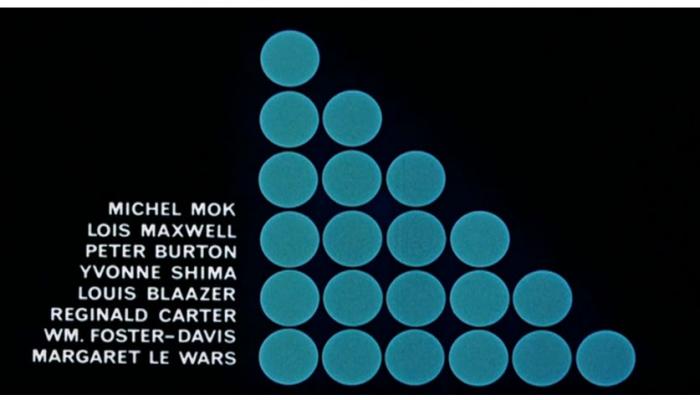
Akzidenz Grotesk geht schon in die richtige Richtung. Aber diese Titelei war damals alles Handarbeit. Eventuell wurde das Alphabet eigens gezeichnet und montiert, vielleicht gab es irgendwelche Fotosatz-Schablonen, wer weiß …
Dass man man jetzt einen heutigen Font benennen kann, der exakt diesen Look erzeugt, glaube ich eher nicht. Zumal die »Rounded-Charakter« ja wahrscheinlich kein Stilmittel sondern Folge der eingesetzten (Abfilm-)Technik war.
Dem J zu urteilen, handelt es sich um die »Gothic 720« von Bitstream und ist z.B. bei FontShop erhältlich.
Für die Gothic 720 finde ich auch nix, aber auch gar nix zum Schriftschneider. Ist die Gothic 720 einfach nur ein generischer Nachbau von den Schriften, wie sie auch im Titel verwendet wurden? Irgendwie erinnert die mich an die alten Monotype-Grotesken, welche auch die Basis für die Arial MT waren. Schon daher würde ich auf eine gewisse Verwandschaft tippen. Paar Schnitte der Gothic 720 findet man auch in jeder der Bitstream Sammlungen die Corel-Software (zB Draw) mitgeliefert wird.
Bitstream hat damals beim »Klauen« fremder Bibliotheken die Namen geändert und eben generische Begriffe with Geometric, Gothic usw. verwendet:
Gothic 720 (BT)
→ Grotesque 126, 215, 216
Gothic 725 (BT)
→ Akzidenz Grotesk
Gothic 762
→ Bell Centennial
Gothic 761
→ Bell Gothic
Gothic 821 (BT)
→  Block
Genau. Auch die Monotype Grotesque aus 1926 ist nicht ganz so originell wie sie uns häufig präsentiert wird. Sie war bei Monotype die Vorlage für die Arial, aber die Grotesque 215 und 216 basieren auf die Venus Grotesk der Bauer’sche Gießerei aus 1907. Das erzählt uns nicht nur der englische Schrifthistoriker James Mosley schon seit längerem, aber inzwischen auch Linotype. Hier noch ein Artikel von Paul Shaw mit ein paar interessante Abbildungen aus dem Leben der Monotype Grotesque und ihre Vorfahren, die Venus Grotesk und die Ideal Grotesk. Auch den Link auf Klimsch Jahrbuch 1907 ist verfolgenswert!
→ Grotesque 126, 215, 216
Die gibts aber nicht digital, oder?
Ich glaube schon, schau mal hier. Die Monotype Schriften haben heute halt keine Seriennummer mehr. Beispielsweise Times New Roman hatte zu Blei- und Fotosatzzeiten die Seriennummer 327. Ich vermute mal, dass sie danach verschwunden sind weil PostScript Type1 Schriften keine Nummern in bestimmte Nameneinträge enthalten konnten.
Hallo Pürsti. »Der Albert« sieht das so: damals war ich Angestellter der Firma Scangraphic. Mit der Klauerei hatte ich aber nicht viel zu tun, das Übel war im Grunde genommen bereits geschehen wo ich da angefangen habe. Inzwischen sind Gott sei Dank die Meisten der nicht-lizenzierten Schriften (das sind die die umbenannt und teilweise auch umgezeichnet wurden) vom Markt genommen worden.
Irgendwie klingt es als ob meinst dass Du zu lange auf eine Reaktion von mir warten musstet. Wenn Du es eilig hast, dann maile mich lieber persönlich, das geht bestimmt schneller.
Nein, hab es überhaupt nicht eilig. Hätt auch nicht nachgehakt wenn Du selber hier nicht recht streng gegen Bitstream geurteilt hättest. Warum Bitstream so als der ganz böse Bube immer hingestellt wird wo doch auch andere heut sich so nobel gebende Foundries vergleichbar agiert haben mag ich halt nicht ganz unkommentiert lassen. Tja und daß Du gar nichts mit dem was Du als „Klauerei“ bezeichnest zu tun hättest nehm ich Dir nicht so ganz ab. Und wenn „das Übel … im Grunde genommen bereits geschehen“ war bleibt die Frage warum Du dort angeheuert hast. Mag hier keinen anprangern nur darf man halt  sich nicht wundern wenn man an den eigenen hier geposteten Maßstäben sich messen lassen muß.
Einige Bitstream-Digitalisierungen sind allerdings den „Original“-Digitalisierungen überlegen. Ein Beispiel dafür ist die Humanist 777, welche die beste Frutiger-Digitalisierung ist, die ich kenne (wobei ich dazusagen muß, daß ich mir die Neue Frutiger nicht näher angesehen habe, ich also nicht weiß, wie sie im Vergleich zur Humanist 777 einzuordnen ist).